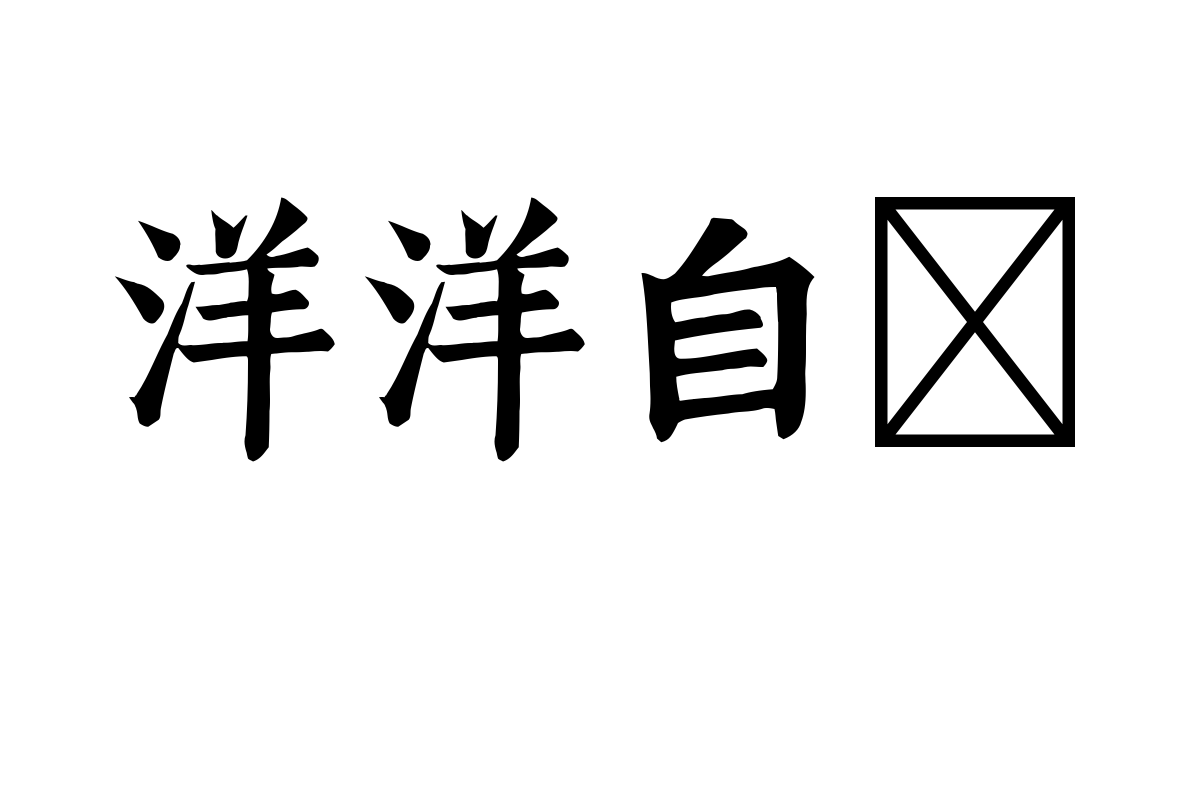
班马字类字体是一种具有现代感和时尚气息的中文字体,它以其独特的设计和风格吸引了许多设计师和品牌的青睐。这种字体的特点在于其简洁明了的线条和结构,以及富有表现力的文字形态。
班马字类字体的笔画流畅自然,没有过多的装饰元素,这使得它在视觉上更加简洁明快。同时,这种字体也具有一定的可读性,无论是在正式场合还是非正式场合都能很好地传达信息。
班马字类字体的设计风格独特,既有现代感又有艺术感。它的线条粗细变化丰富,能够营造出不同的视觉效果。此外,这种字体也具有较强的适应性,可以应用于各种类型的设计作品中,包括海报、宣传册、网站等。
总的来说,班马字类字体是一种非常实用且具有吸引力的中文字体,适合用于各种设计项目。